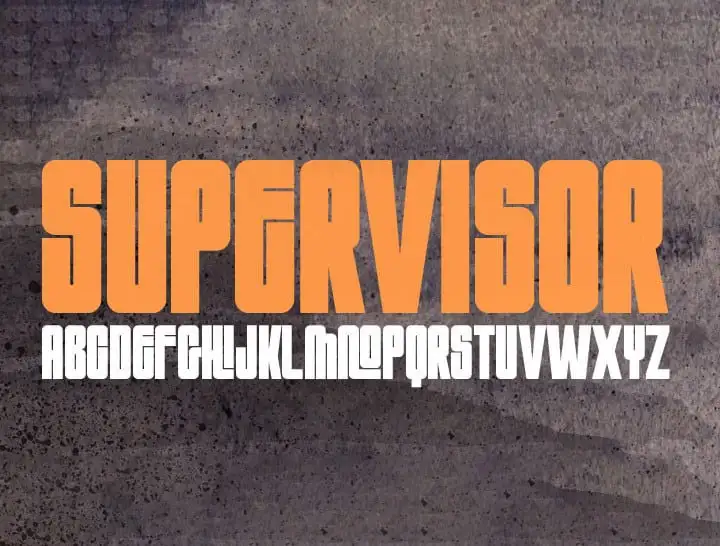
Supervisor Display Font – Download Grátis
A fonte Supervisor Display é uma seleção perfeita para aqueles que valorizam design minimalista e funcionalidade pura. Seu alto contraste torna-a ideal para aplicações visuais que requerem destaque, como logotipos de marca ou títulos em cenários publicitários. A ideia por trás dessa fonte é explorar o encanto dos padrões geométricos retos e limpos, maximizando a utilização do espaço enquanto mantém os espaços vazios ao menor possível. O resultado é uma família de tipo display que não apenas estabelece um olhar impactante, mas também manter-se atrativo e envolvente para o leitor. Tudo isso sem perder a legibilidade essencial, tornando-a perfeita para situações onde deseja destacar seu conteúdo enquanto mantém as pessoas focadas em suas mensagens. Ideal tanto para aplicativos digitais quanto impressos, esta fonte é uma escolha ótima para designers e criadores de conteúdo que buscam um toque moderno e assertivo em seus projetos. Com design minimalista e funcionalidade, Supervisor Display oferece o ideal entre a praticidade e a simplicidade visual.